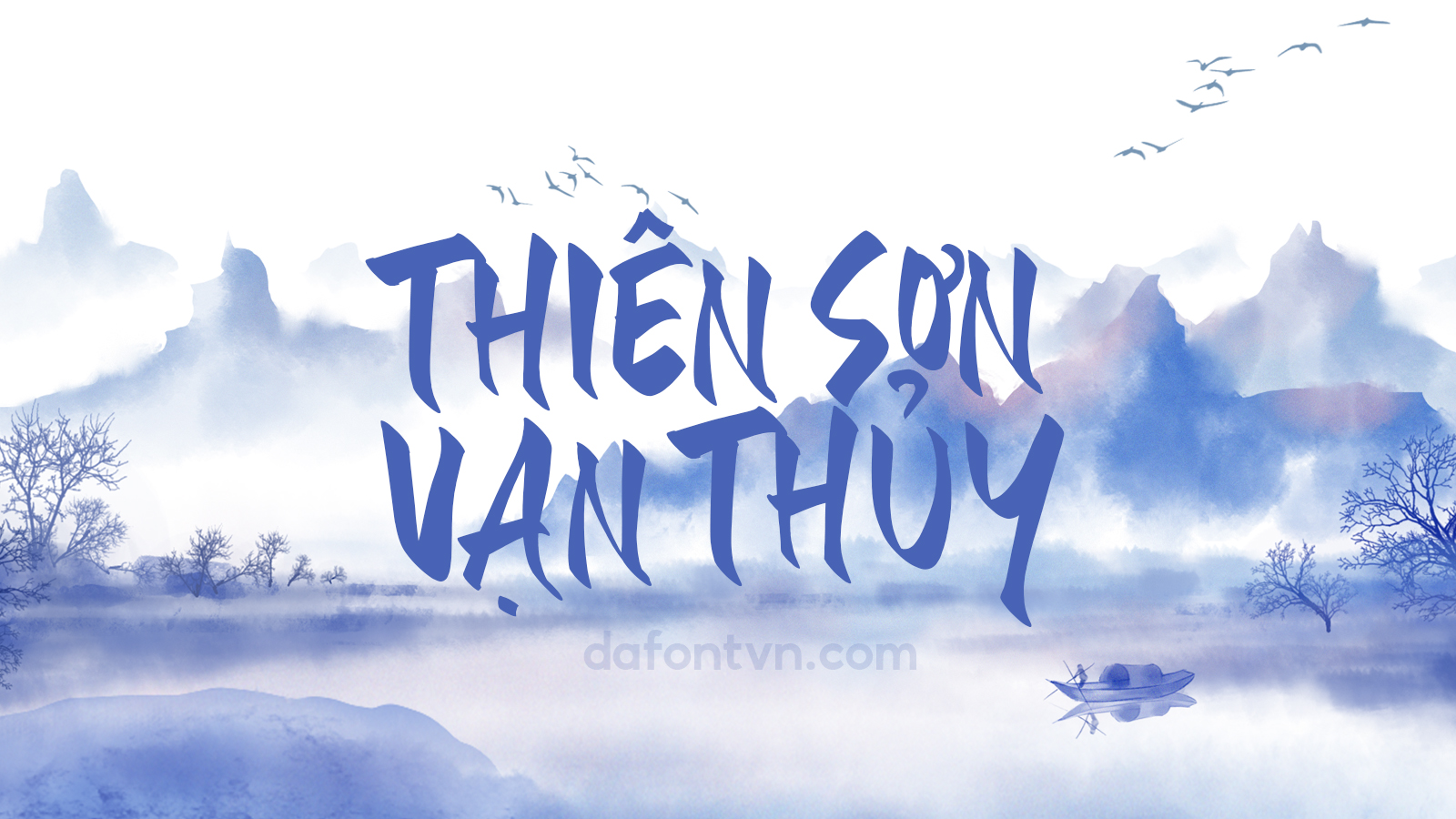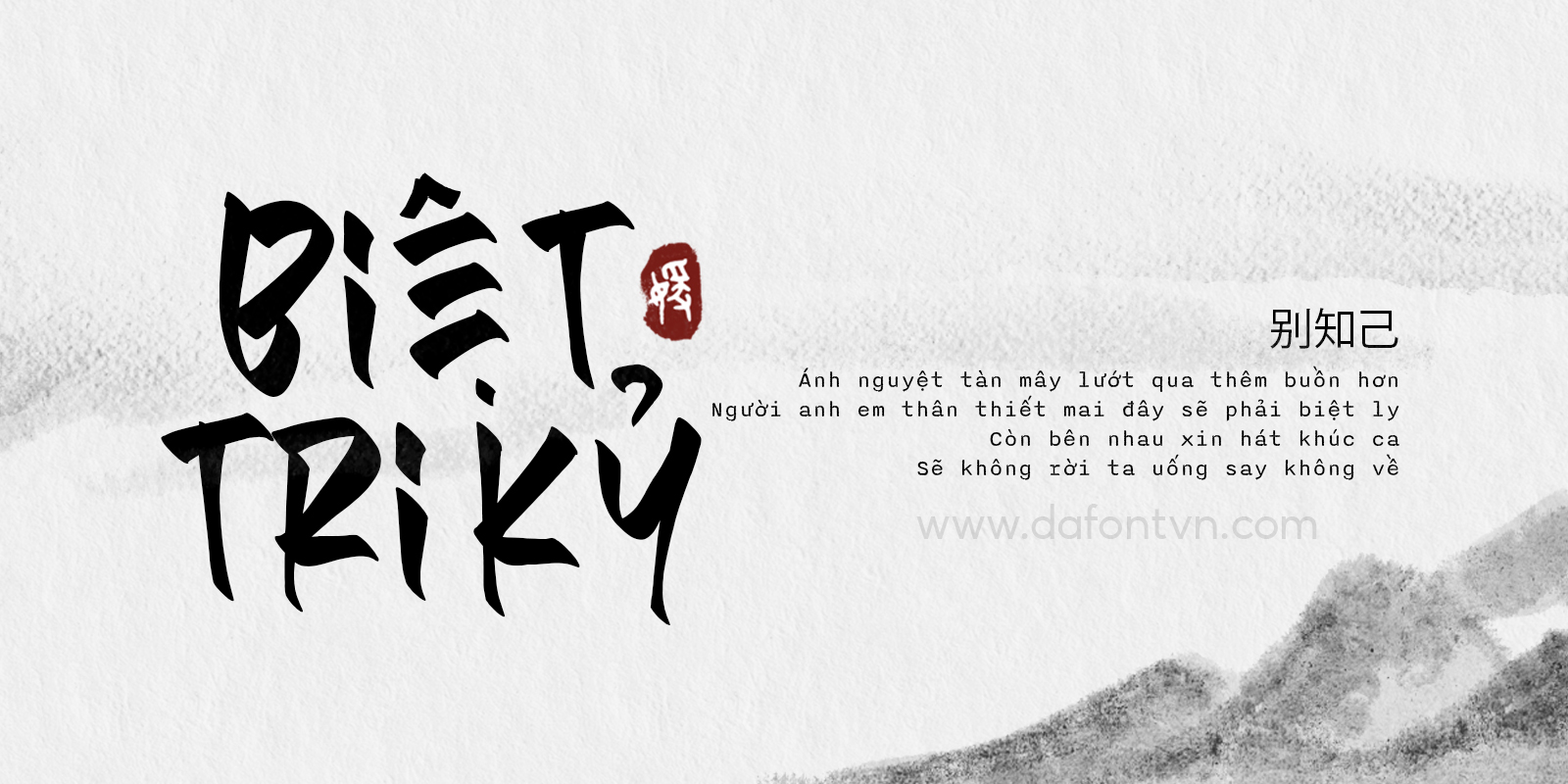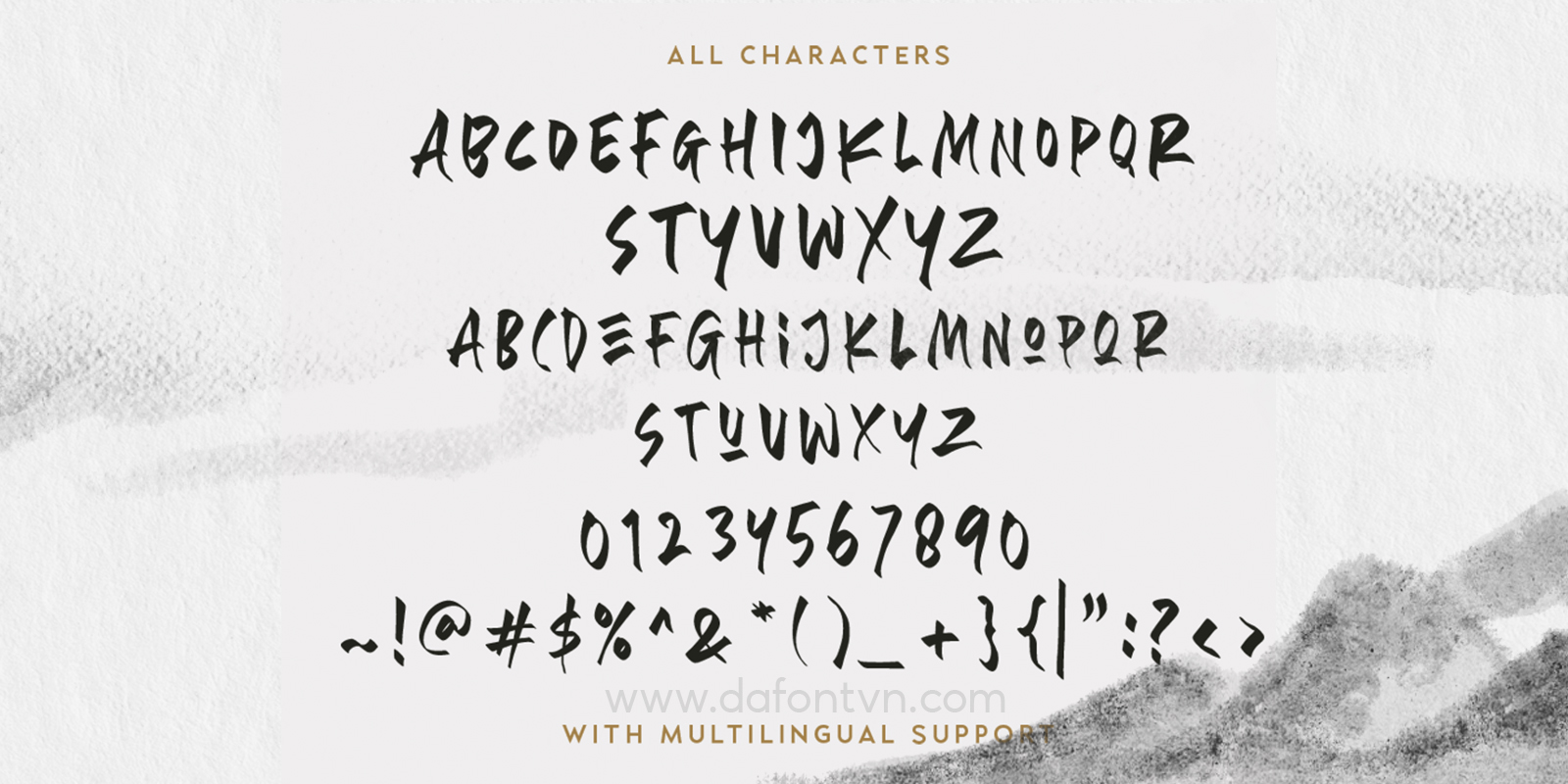
Font Designors Việt Hóa – Font cổ trang việt hóa
Font Designors Việt Hóa là một font chữ đơn giản mang phong cách tự do . Bạn có thể sử dụng phông chữ này cho thiết kế cổ trang hoặc bất kỳ dự án nào. Với chữ thường và chữ hoa khác nhau sẽ làm cho thiết kế của bạn tự nhiên hơn.
Font không có các ký tự thay thế nhưng ý tưởng thiết kế là của bạn vì vậy hãy tận dụng font chữ tốt nhất nhé.